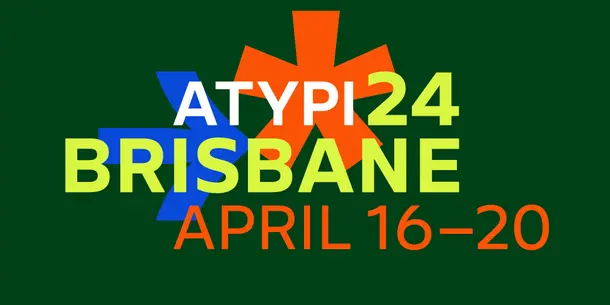
Monotype、タイポグラフィと書体デザインを専門とする国際カンファレンスAtypIに参加
2024 年4 月15 日――米国 Monotype Imaging Inc. の日本法人 Monotype 株式会社(東京都港区、 以下 Monotype)のシニア・タイプデザイナー土井遼太と中国のタイプデザイナーTao Di(タオ・ディ)が、2024 年4 ⽉ 16 ⽇(火)から20 ⽇(⼟)までオーストラリア・ブリスベンで開催されるタイポグラフィとタイプデザインの国際カンファレンス「ATypI Brisbane 2024」に参加します。
プレゼンテーションの内容
「中国と日本のタイプトレンド」 中国と日本は多くの表意文字(中国では汉字、日本では漢字)を共有していますが、書体のトレンドは必ずしも同じではありません。例えば、中国ではテック企業を皮切りに、多くの企業がカスタム書体を採用しはじめています。一方、日本では自動車産業を含むさまざまな分野でカスタム書体の需要が増加しています。それぞれの業界で好まれる書体には特定のトレンドがあります。また、グラフィックデザインとウェブデザインの分野でも、違った傾向が見られます。このプレゼンテーションでは、最新の中国と日本市場のトレンドに関する調査結果や具体例を共有し、両国の市場動向の類似点と相違点について詳しく探ります。
AtypI とは
ATypI (Association Typographique Internationale) は、タイポグラフィーと書体デザインを専門とする国際的な非営利団体です。1957年以来、毎年異なる都市でカンファレンスが開催され、タイポグラフィーとタイプデザインのアイデアや研究を発表しています。さらに、テクノロジーと教育に焦点を当てた ATypI ワーキングセミナーも数多く開催し、2013年以来、カンファレンスのアーカイブビデオを公開しています。
シニア・タイプデザイナー 土井遼太
東京藝術大学デザイン科を卒業後、英国レディング大学書体デザインコースで修士号を取得。2015 年よりタイプデザイナーとしてMonotype に在籍し、企業制定書体の開発や、書体選定をはじめとしたコンサルティングを行う。また、たづがね角ゴシックの制作メンバーとして、ファミリー展開やCJK(中日韓)言語に対応 した字種拡張にも携わる。最近では、大学での講義や国際カンファレンスでの登壇を通じ、国内外に向けて書 体についての発信をしている。
これまで携わった書体やプロジェクト:
Shorai Sans
たづがね角ゴシック
Mitsui and Co sans
タイプデザイナー Tao Di
Monotype 上海の書体デザイナー。大学では工学を専攻。卒業後はグラフィックデザイナーとし て中国の広告代理店に就職。このとき書体の魅力に取りつかれ、独学で書体デザインを勉強する。Monotype 入社以前は中国最大の書体ファウンドリー、方正字库のデザイナーとして、専用書体を含め数多くの書体の開 発に携わる。
これまで携わった書体やプロジェクト:
Shorai Sans
Garena Sea Group: GFF
Type Great Wall Motor Company Limited: GWM Sans